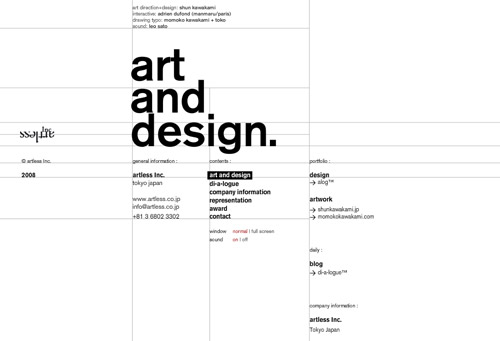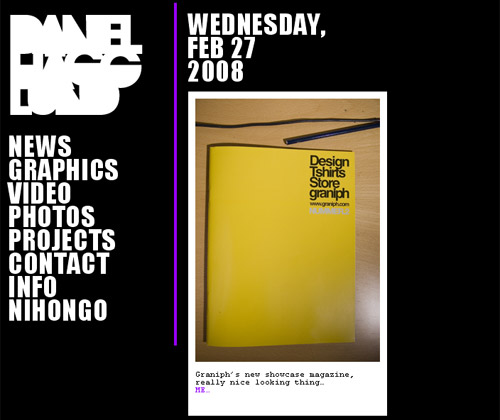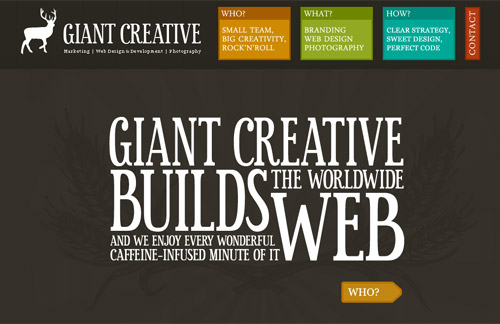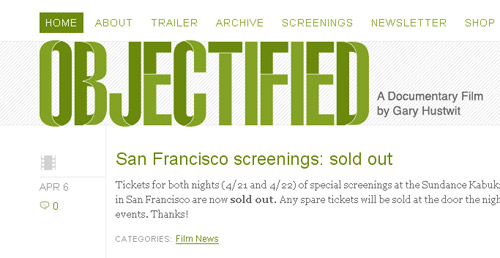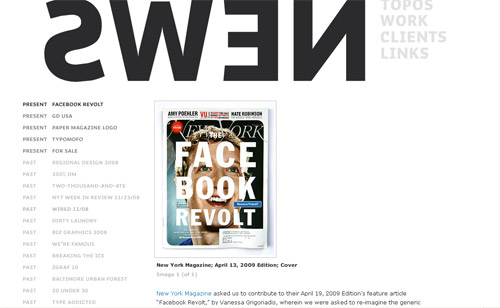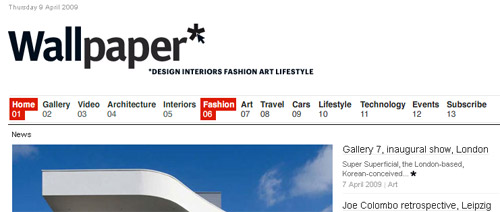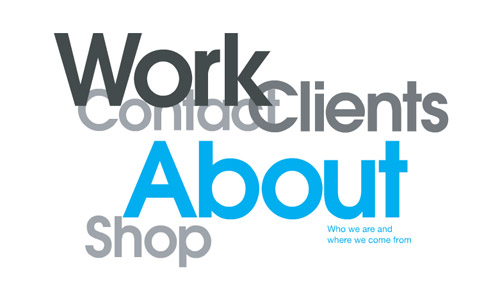
Le tendenze della tipografia nel Web
La tipografia nel web stà diventando sempre più elemendo di design, visivamente elegante attira l'attenzione dell'utente non diventando mai pacchiana...
Una tendenza che è stata iniziata con il famoso Web2.0 (e da pochi precursori) e che si stà facendo prepotente in questo 2009 è quella di usare la tipografia nel web come elemento di design, ingigantendo, incastonando e posizionando al centro della progettazione testi e caratteri riuscendo cosi a creare un design attraente e funzionale che nella maggior parte dei casi attira l’attenzione dell’utente senza però risultare pacchiano o fastidioso.
In particolare i font che si stanno rilevando più utili in questo nuovo utilizzo sono quelli con linee geometriche semplici, nitide e precise.
Ma vediamo qualche sito internet dove web e tipografia si uniscono in perfetta armonia:
Wallpaper
Pier Madonia
Giant Creative
Objectified
300 MIlion
Daniel Hagglund
Artless Inc.
Toposgraphics